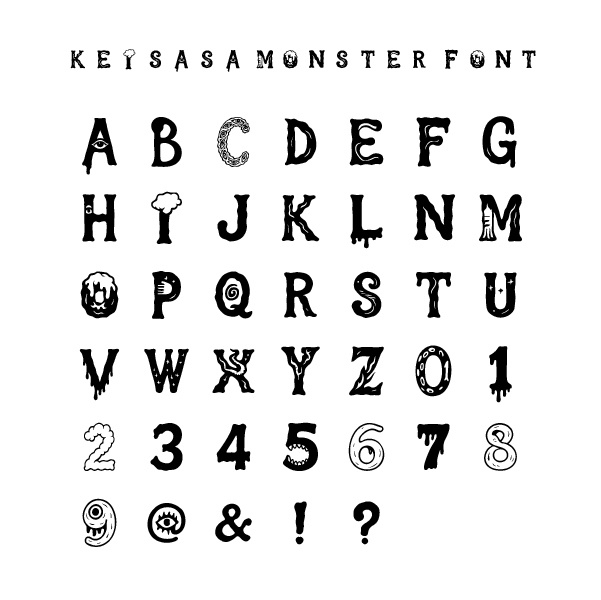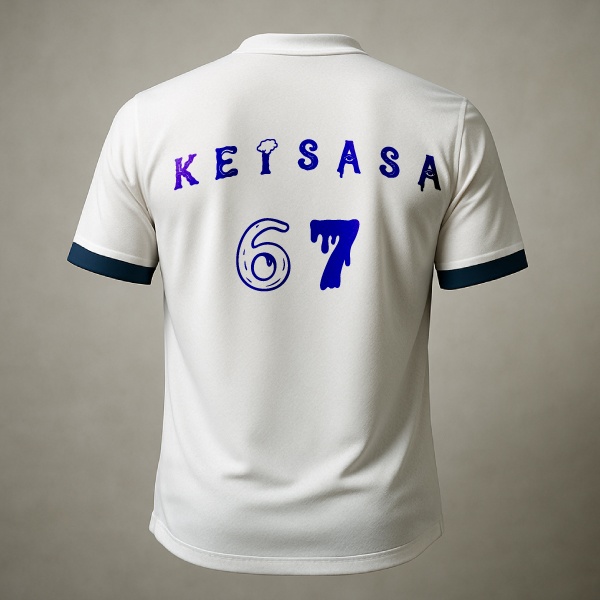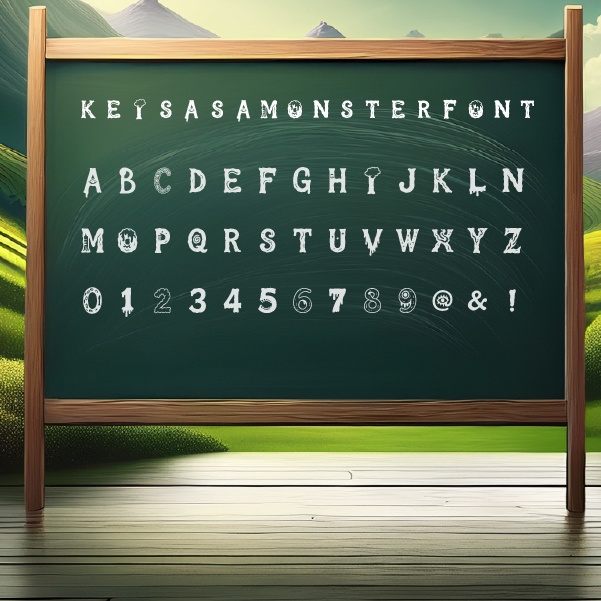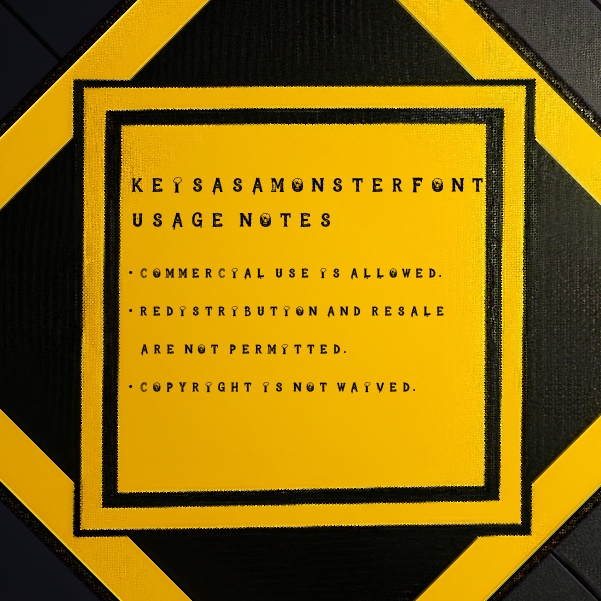
【商用可】Keisasa monster font.ttf|サイケ風モンスターフォント
👁 keisasa_monster_fontとは? 記号は、見ている。 このフォントは、英数字や記号たちが「意思を持つ怪物」となったような、 奇抜でアート性の高いモンスターフォントです。 1文字打つだけで、作品にストーリーと"目線"が生まれます。 🔤 収録文字 A~Z(大文字のみ/すべて手描き変形) 0~9(個性豊かな数字モンスターたち) 記号:!?@& ※小文字・ひらがな・カタカナは未収録です。 商用利用OK(クレジット任意) 再配布・改変フォントの再配布NG This is an original TTF font designed by Japanese artist Keisasa. Available for commercial use. Ideal for creative design, games, and more.